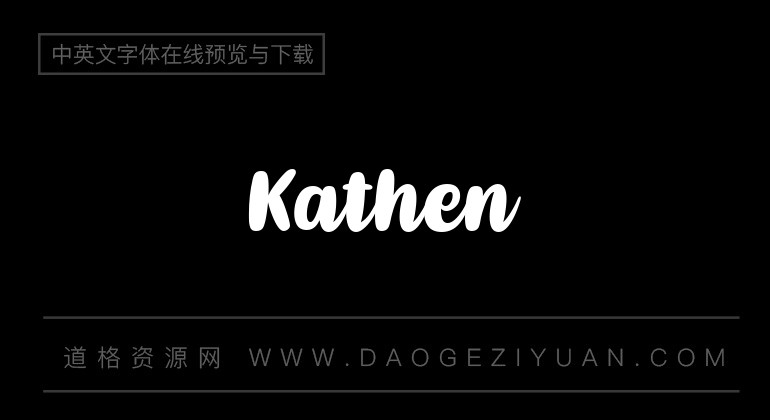
Kathen
Kathen 字体是一款简洁、时尚、优雅的英文字体,它具有清晰的线条与流畅的笔画,拥有舒适的字形,可以让你的文字更加精致。它的字体风格细腻而又不失优雅,适合用于各种设计、排版和平面设计中。它的字体设计灵感来自于古典艺术,给人以温柔、柔和的感觉,可以让你的文字更加精致。
Kathen是一款非常不错的手写艺术字体,具有很好的视觉感,适合于文化类的宣传设计、商业类品牌的广告和产品包装设计以及个性化文字排版等较多场景。